טיפוגרפיה אומנותית היא לא רק בחירה של אותיות, אלא עולם שלם של אמנות היוצר שפה חזותית ייחודית. כל פונט, כל אות היא יצירה בפני עצמה הנושאת עמה מסר, תחושה ואפילו אישיות.
במאמר זה נצלול לעולם המופלא של עיצוב פונטים, נגלה קצת מהסודות והטכניקות שמאחורי יצירת פונטים ייחודיים, ונדבר על ההשפעה של הטיפוגרפיה אומנותית על העיצוב הגרפי.
מהי טיפוגרפיה אומנותית?
טיפוגרפיה היא אמנות עתיקה, שורשיה הולכים אחורה עד כתבי היד הראשונים. עם השנים, הטיפוגרפיה התפתחה והתחדשה, והיום היא חלק בלתי נפרד מעולמות העיצוב הגרפי.
גם בעידן הדיגיטלי בו עיצוב פונטים הפך להיות נגיש יותר, ומעצבים רבים יוצרים פונטים ייחודיים לפרויקטים שונים, העיצוב עדיין מתבסס על האמנות העתיקה הזו.
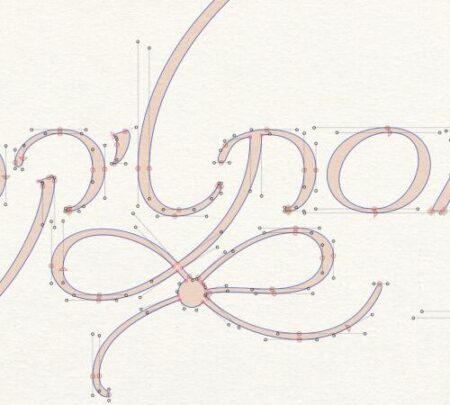
כמה הבנות חשובות על פונטים:
- פונטים בעברית הם עולם שלם בפני עצמו. עולם אחר. האותיות העבריות, על צורותיהן המורכבות והקונוטציות ההיסטוריות שלהן, מעמידות לרשותנו אפשרויות יצירה אינסופיות.
יש לא מעט מעצבים המתמחים בעיצוב פונטים בשפה העברית, ומשלבים בצורה עדינה ומופלאה בין המסורת לבין חדשנות.
- פונטים מומלצים בעברית אינם עניין קבוע, ההמלצות שלנו משתנות בהתאם לסגנון העיצוב ולמטרה שלו. ישנם פונטים קלאסיים, המשמשים לעיצוב טקסטים ארוכים, וישנם פונטים מודרניים, המתאימים לעיצוב גרפי עכשווי.
מה שכן, אל תזלזלו בכלל בשלב הזה. בחירת הפונט המתאים היא שלב קריטי בתהליך העיצוב, שכן היא גורם מספר אחת בהשפעה על האופן שבו הקורא תופס את הטקסט.
- טיפוגרפיה יהודית היא תחום עשיר ומרתק, המשלב בין המסורת היהודית לבין עיצוב מודרני ומעצבים רבים שואבים השראה מכתבי היד העבריים, מהקישוטים והעיטורים המסורתיים.
הם יוצרים פונטים מרהיבים וייחודיים בעלי אופי משל עצמם, המשקפים את הזהות היהודית ואת רוח היצירה והאמנות שלהם.
- פונטים פופולריים בעברית משתנים עם הזמן. מה שהיה פופולרי לפני עשור, עשוי להיות בהחלט פחות רלוונטי היום.
יחד עם זאת, ישנם פונטים קלאסיים ויחסית שגרתיים שנותרו פופולריים במשך שנים רבות, בעיקר בשל הפונקציונליות הטובה שלהם, ובמקביל אליהם מתפתחים כל העת פונטים חדשים שצוברים פופולריות רבה בקרב מעצבים צעירים.
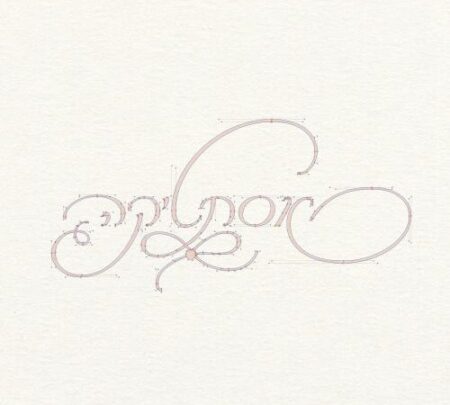
טכניקות לעיצוב פונטים ייחודיים:
- חקר ההיסטוריה: היכרות עם ההיסטוריה של הטיפוגרפיה, כמו גם זו של האותיות העבריות, יכולה לספק השראה ולהוות עזרה משמעותית ביצירת פונטים ייחודיים.
- ניסוי, תעייה וחיפוש: אל תפחדו לנסות דברים חדשים ולשחק עם צורות האותיות. בכלל, תסכימו איתנו שהאומץ לנסות דברים חדשים בדרך כלל מוביל אותנו למקומות יפים בחיים ולהצלחות.
- הקשר בין צורה לתחושה: כל צורה מעבירה תחושה מסוימת. חשבו על התחושה שאתם רוצים להעביר באמצעות הפונט שלכם, היא תוביל אתכם לצורה הרצויה.
- הקשר בין פונט לתמונה: פונטים נוטים לשמש גם ככלי להעברת מסר חזותי. אז חשבו גם על התמונה שאתם רוצים ליצור באמצעות הפונט. שאלו את עצמכם מה אתם רוצים שהצופה יראה בעיניו, ובהתאם לכך תצרו את הפונט.
- שימוש בצבע: צבע הוא כלי רב עוצמה בעיצוב פונטים. צבעים מעבירים תחושות, וצבעים שונים מעבירים תחושות שונות. תקשיבו לצבעים, שמעו מה הם מדברים, ובחרו בהתאם.
- שימוש במרקמים: מרקמים יכולים להוסיף עומק ועניין לפונט. אל תוותרו עליהם.
- שימוש באפקטים: אפקטים כמו צל, הילה או הטייה יכולים להוסיף נופך אישי לפונט, וגם המון יופי ויזואלי וגוון ייחודי.
לסיכום
טיפוגרפיה אומנותית היא תחום מרתק ודינאמי, המציע אפשרויות יצירתיות אינסופיות. על ידי הבנת העקרונות הבסיסיים של הטיפוגרפיה והתנסות בפועל בטכניקות שונות, תוכלו ליצור פונטים ייחודיים, יפהפיים ומקוריים, שיעבירו את המסר שלכם בצורה ברורה ויעילה.
כדי להעמיק את ההבנה שלכם בתחום, אני ממליצה לכם לעקוב ולחקור את עבודותיהם של מעצבי פונטים מובילים, לעשות שיטוט לימודי כאן באתר, לא לפחד להוציא כסף על קורסים וסדנאות, ובעיקר לנסות בפועל ליצור פונטים משלכם בהשראה של טיפוגרפיה אומנותית.
טיפוגרפיה אומנותית – שאלות נפוצות
מה ההבדל בין טיפוגרפיה אומנותית לטיפוגרפיה רגילה?
טיפוגרפיה אומנותית היא למעשה תת-קטגוריה של הטיפוגרפיה הרגילה, אך עם דגש חזק יותר על היבטים אסתטיים ויצירתיים.
בעוד הטיפוגרפיה הרגילה שמה דגש על קריאות ופונקציונליות, זו האומנותית מרחיבה את גבולות העיצוב ומאפשרת למעצבים לחקור ולנסות סגנונות וטכניקות שונות.
פונטים אומנותיים משמשים לעיתים קרובות ביישומים גרפיים יצירתיים כמו לוגואים, פוסטרים ואמנות דיגיטלית, ולאו דווקא בטקסטים ארוכים.
כיצד אוכל ללמוד יותר על עיצוב פונטים?
ישנן מספר דרכים ללמוד יותר על עיצוב פונטים:
- קורסים וסדנאות: ניתן למצוא קורסים מקוונים ומפגשים פרונטליים העוסקים בעיצוב פונטים, החל ברמות התחלתיות ועד לרמות מתקדמות.
- ספרים ומאמרים: ישנם ספרים רבים ומאמרים מקצועיים העוסקים בטיפוגרפיה ועיצוב פונטים.
- תוכנות לעיצוב פונטים: תוכנות כגון FontForge ו-Glyphs מאפשרות לך ליצור ולערוך פונטים באופן עצמאי.
- קהילות מקוונות: הצטרפות לקהילות מקוונות של מעצבי פונטים, פורומים ובלוגים יכולה לספק לך השראה, ידע וכלים שימושיים.
- תרגול: הדרך הטובה ביותר לשלוט בעיצוב פונטים היא באמצעות תרגול. התחל בפרויקטים קטנים והתקדם בהדרגה לפרויקטים מורכבים יותר.